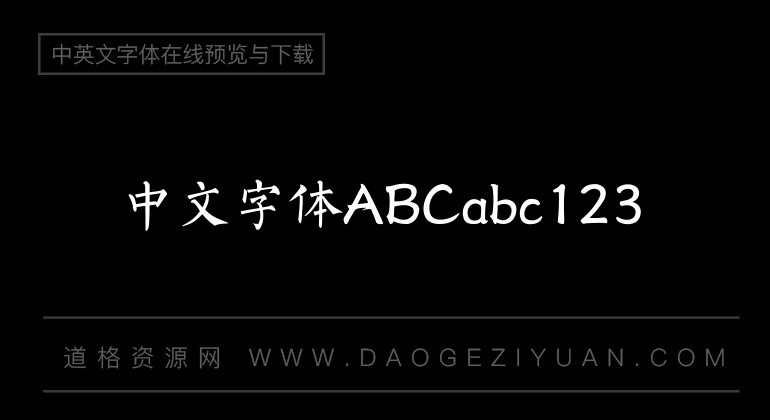
方正苏新诗柳楷简体字体是由方正字库设计师苏新先生创作的一款书法字体。该字体结合了楷书和草书的特点,具有流畅的书法笔画、结构饱满、线条流畅等特点,同时字形简洁大方,适合用于正式场合的印刷、书写等。方正苏新诗柳楷简体字体包含了常用的汉字、标点符号、数字等字符,可用于印刷、出版、广告、宣传等方面。文件名:方正苏新诗柳楷简体
方正苏新诗柳楷简体是一款非常不错的手写艺术字体,具有很好的视觉感,适合于文化类的宣传设计、商业类品牌的广告和产品包装设计以及个性化文字排版等较多场景。